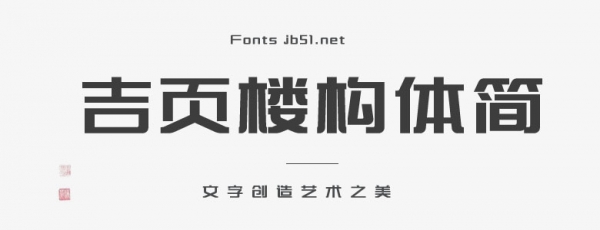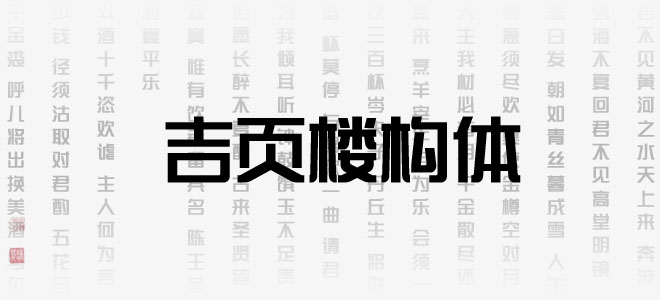
吉頁(yè)樓構(gòu)體簡(jiǎn)是一款書(shū)寫(xiě)很新穎的字體,字體大方,適合應(yīng)用于藝術(shù)設(shè)計(jì)、平面宣傳設(shè)計(jì)、網(wǎng)頁(yè)設(shè)計(jì)、書(shū)法字體,海報(bào)設(shè)計(jì)等領(lǐng)域,歡迎喜歡這款字體的朋友下載收藏。
吉頁(yè)樓構(gòu)體簡(jiǎn)